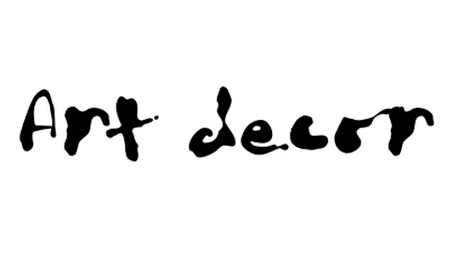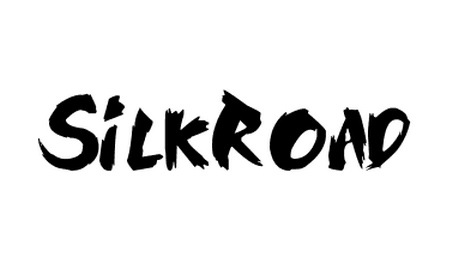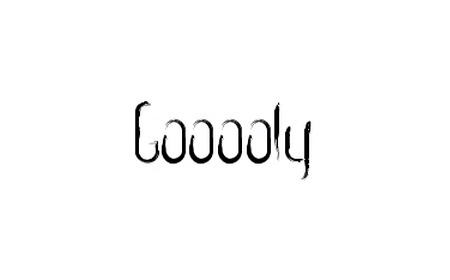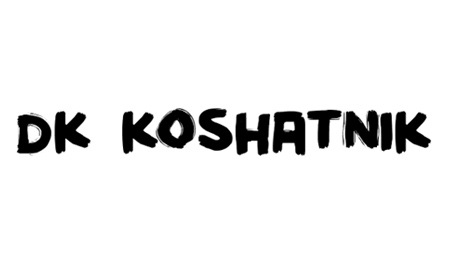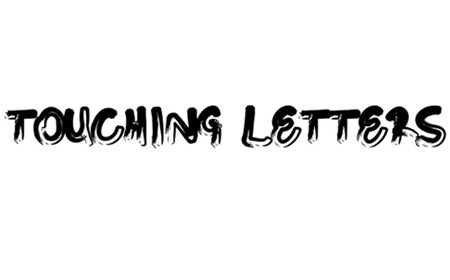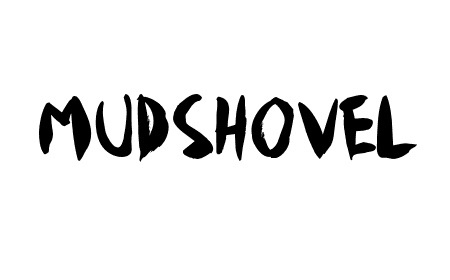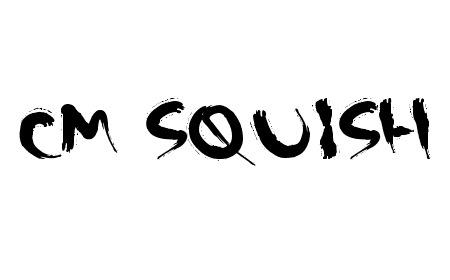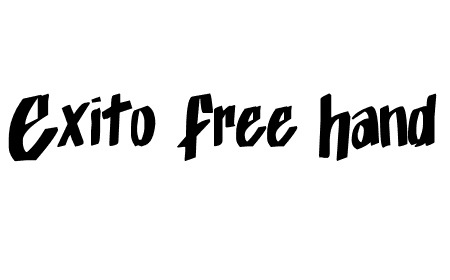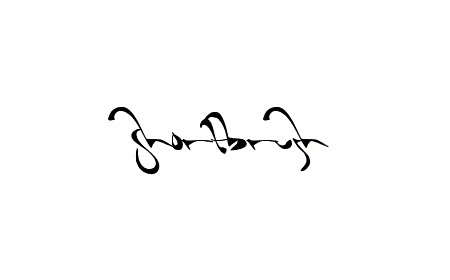
42 бесплатных стильных шрифта-кисти
шрифты-кистиБыло множество комментариев к подборкам связанным с шрифтами. Многие из вас интересуются, можно ли использовать их в кириллическом написании.  Да, далеко не все из них могут использоваться в сочетании с кириллицей, но и дизайны все больше создают с латинской типографикой. В этой подборке, мы представим вашему вниманию шрифты-кисти. Такие шрифты часто используют в печатных изданиях, что придает им особый и неповторимый стиль. Неровности, размытость, толщина, потеки краски, придут обаяния любому проекту.
Тут вы найдете 42 бесплатных шрифта-кисти. Жирные, тонкие, округлые шрифты, шрифты в арабском, японском, гранж и готическом стилях, все это вы увидите в этой подборке и сможете загрузить абсолютно бесплатно.
Шрифт-кисть “Levi”
Шрифт-кисть
Крупный шрифт
Крупный шрифт
Шрифт краской “Appo”
Шрифт краской
Шрифт нарисованный кистью
Шрифт нарисованный кистью
Шрифт кистью
Шрифт кистью
Шрифт кистью в стиле дудл
Шрифт кистью в стиле дудл
Жирный шрифт
Жирный шрифт
Шрифт с наклоном в лево
Шрифт с наклоном в лево
Красивый прописной шрифт кистью
Красивый прописной шрифт кистью
Шрифт в печатном стиле
Шрифт в печатном стиле
Прописной шрифт пером
Прописной шрифт пером
Шрифт в стиле гранж
Шрифт в стиле гранж
Шрифт печатными буквами
Шрифт печатными буквами
Шрифт в стиле набросков
Шрифт в стиле набросков
Урбанистический шрифт
Урбанистический шрифт
Жирный шрифт с потеками краски
Жирный шрифт с потеками краски
Кривой шрифт
Кривой шрифт
Шрифт краской
Шрифт краской
Шрифт прописью с потеками
Шрифт прописью с потеками
Крупный жирный шрифт
Крупный жирный шрифт